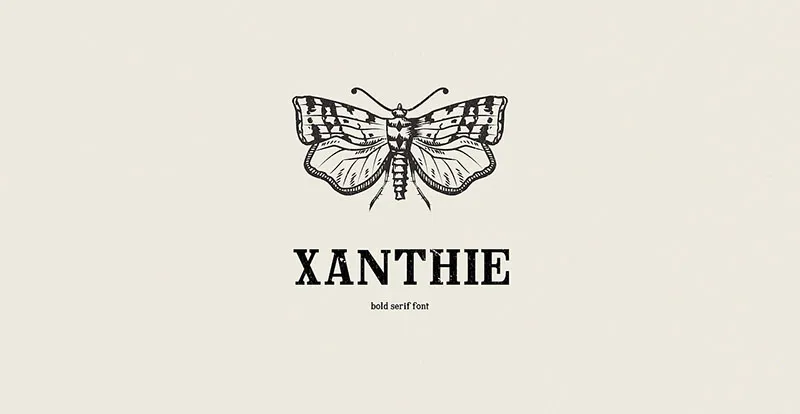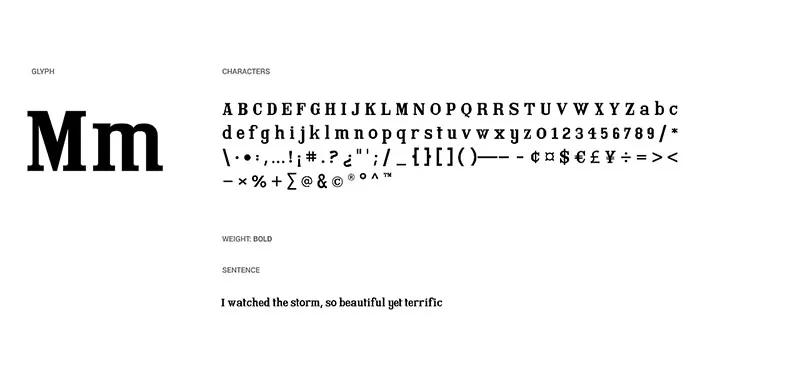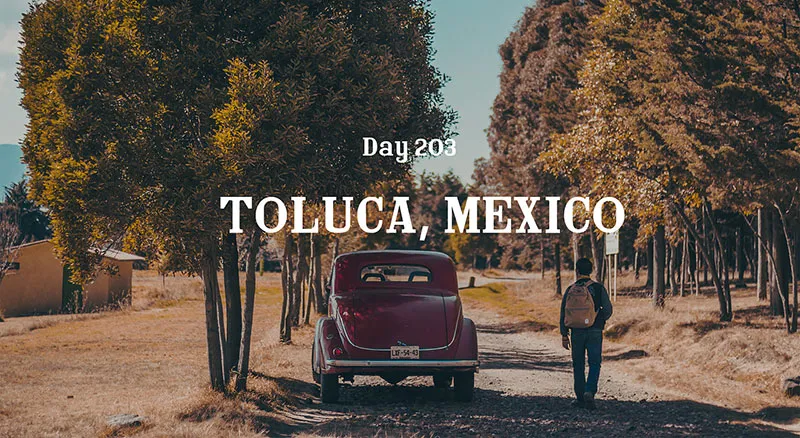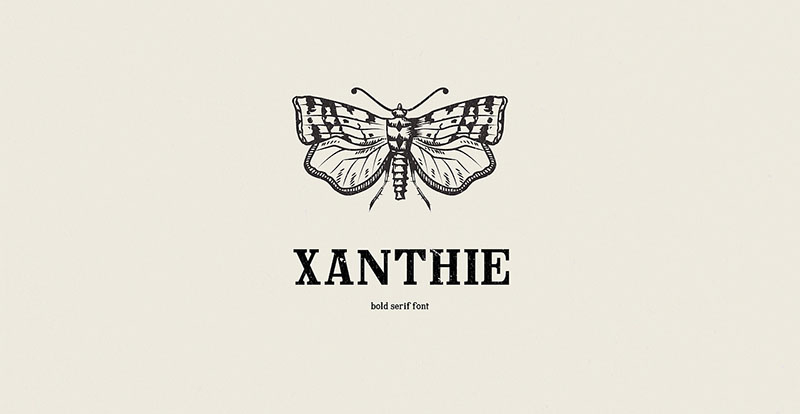
Xanthie是一種襯線字體,有懷舊的感覺。它的靈感來源於一本面向兒童的公共領域經典法語字母學習書。Xanthie是一種特別適合需要大標題的設計的字體。
字體名稱:Xanthie
設計:Simo Herold
Xanthie is a serif font with a nostalgic feel. It is inspired by a public domain vintage French alphabet learning book for children. Xanthie is a font suitable especially for designs needing big headings.
Font Name: Xanthie
Designed by: Simo Herold